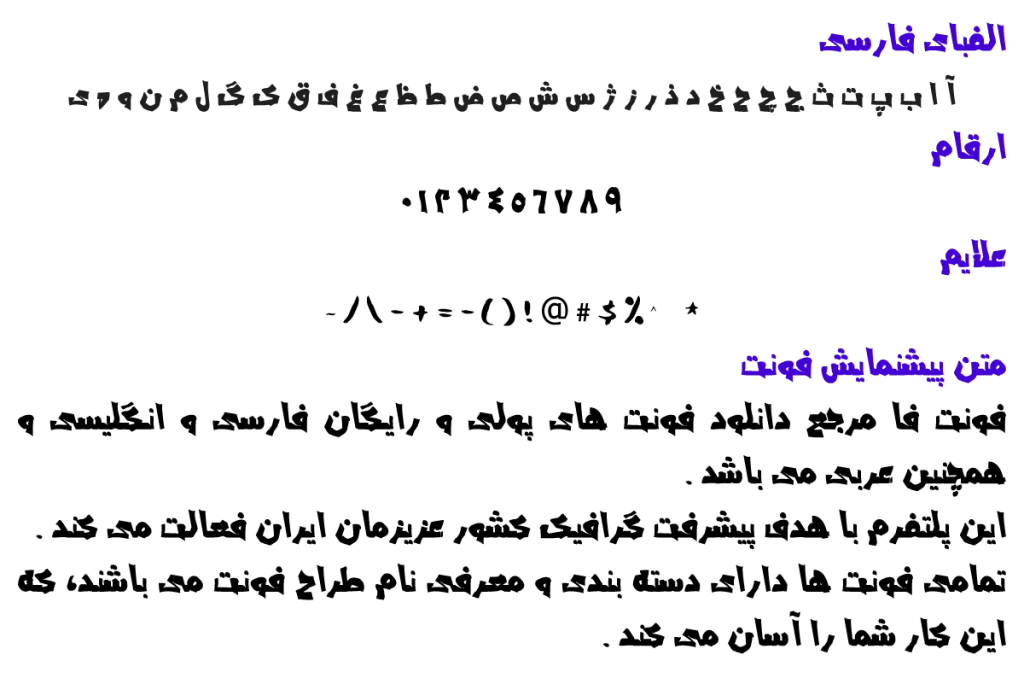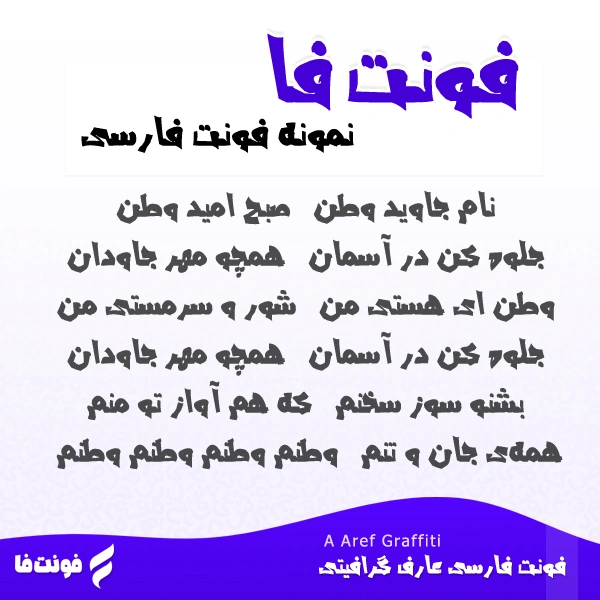
فونت فارسی عارف گرافیتی – A Aref Graffiti
پیشنمایش فونت عارف گرافیتی
توضیحات و معرفی فونت عارف گرافیتی
فونت فارسی عارف گرافیتی ( A Aref Graffiti ) از مجموعه فونت های آزاد می باشد، همینطور نوع فونت گرافیکی می باشد.
فونت زیبای مرتبط توسط عبد الله عارف در سال 1390 طراحی و ساخته شده است.
نمونه ی تصویری زیر، تایپ فیس را در ترکیب با شعری میهن دوستانه نمایش میدهد.